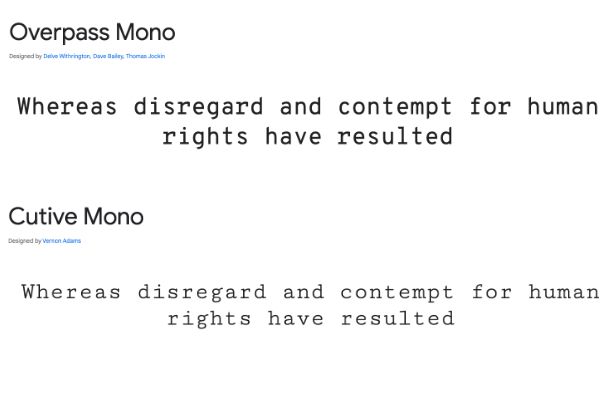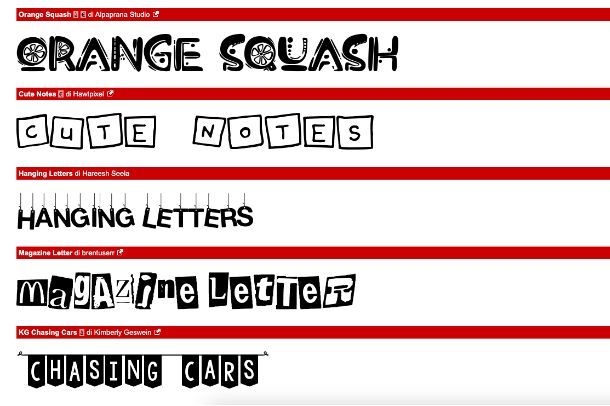
Migliori font per siti Web
Stai realizzando un piccolo sito Web per promuovere la tua attività o come tuo semplice portfolio personale, e grazie ai consigli presenti nel mio tutorial sei riuscito a realizzare il tutto senza particolari problemi.
Adesso, dunque, stai finalizzando il tutto, andando ad apportare le ultime modifiche grafiche. Infatti, nonostante le immagine e i colori utilizzati ti soddisfino pienamente, non puoi dire la stessa cosa del font utilizzato, per cui hai deciso di cambiarlo. Dato che non avevi idea su quale font utilizzare, hai deciso di metterti sul Web alla ricerca dei migliori font per siti Web e ti sei imbattuto in questo mio tutorial sull'argomento.
Posso dirti che sei capitato nel posto giusto. Nel corso di questa guida ti parlerò dei migliori font da utilizzare sui siti Web e ti mostrerò anche dove poterli scaricare gratuitamente. Tutto quello che devi fare è metterti comodo, prenderti cinque minuti di tempo libero e proseguire con la lettura dei prossimi paragrafi. Non mi resta che augurarti una buona lettura!
Font per siti Web gratis
Non vedi l'ora di scoprire quelli che sono i migliori font per siti Web gratis? Allora non devi far altro che dare un'occhiata ai prossimi paragrafi, dove ti parlerò di quelli più utilizzati e in voga per realizzare un sito Web dalla grafica accattivante.
Font Sans Serif
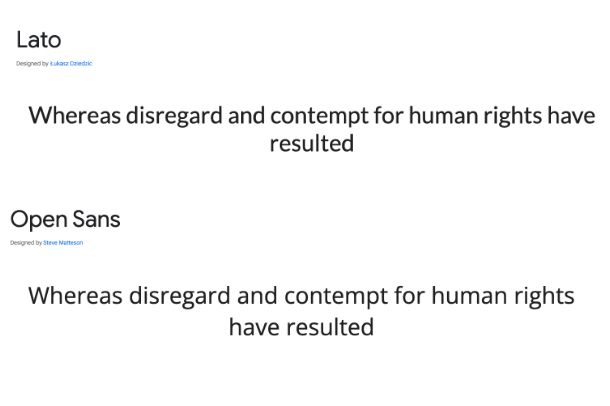
I font Sans Serif rappresentano una famiglia di caratteri dall'aspetto moderno, ma la tempo stesso sono semplici e lineari. Per questo motivo, sono perfetti per realizzare un sito Web tramite il quale si vuole trasmettere professionalità, come ad esempio quello di un'azienda. Inoltre, hanno un alto livello di leggibilità e rendono il tuo sito Web al passo con i tempi.
- Lato – uno dei font più utilizzati nel Web grazie alla sua alta leggibilità che lo rende perfetto per l'utilizzo su tutti i tipi di dispositivi.
- Open Sans – font commissionato da Google ottimizzato per la leggibilità su siti Web e dispositivi mobili, infatti viene utilizzato di default su Mozilla Firefox e nell'app Telegram Desktop.
- Helvetica – font molto classico ed elegante, che ha avuto grande successo negli ani settanta. Tantissime aziende utilizzano questo carattere nel proprio logo, tra cui Microsoft e Motorola.
- Montserrat – font che combina eleganza a elementi di rotondità, che prende ispirazione da vecchi manifesti e insegne del quartiere Montserrat di Buenos Aires.
- Arial – font molto famoso, utilizzato principalmente su PC, infatti è utilizzato all'interno di Microsoft Windows e macOS.
- Noto Sans — font classico utilizzato per qualsiasi tipologia di sito Web, dotato di più stili corsivi, spessori e larghezze.
- Oxygen – font che trasmette innovazione e professionalità, creato come parte del progetto KDE su Linux.
- Roboto – carattere sviluppato da Google, una scelta sicura per qualsiasi Web designer. Utilizza delle forme in gran parte geometriche, ma con alcune curvature che rendono la lettura più piacevole.
- Josefin Sans – font che si ispira ai disegni geometrici degli anni '20, che combina geometrie ed eleganza, con un tocco vintage, consigliato per l'uso in formati più grandi.
- Futura – font molto antico, infatti il suo sviluppo risale addirittura al 1927. Avendo un'altezza piuttosto bassa, è sicuramente più adatto per l'utilizzo all'interno del corpo del testo, piuttosto che sui titoli.
- Questrial – font moderno che rende altamente leggibile il testo, per cui è molto adatto per quei siti Web dotati di pagine con tanto testo e per i titoli.
- Archivo – font progettato per far risaltare le parole chiave e i titoli e che supporta oltre 200 lingue.
- Century Gothic – font in stile geometrico basato sul cerchio e sul quadrato, destinato a usi a caratteri grandi come intestazioni.
- Exo – font dall'aspetto futuristico, ma con un design elegante. Si tratta di un carattere molto versatile, infatti ha 9 pesi, ognuno con una vera versione in corsivo. Funziona bene per testi di piccole e medie dimensioni.
Font Serif
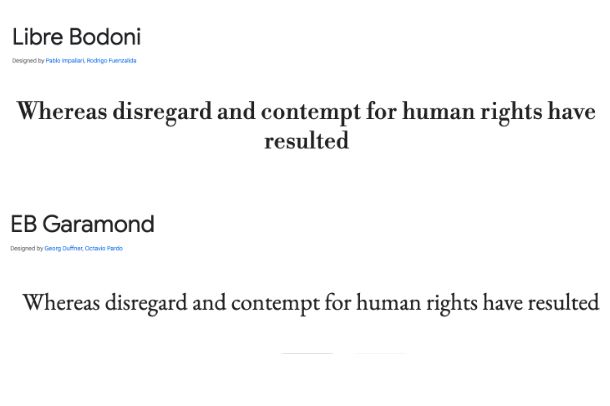
I font Serif, invece, rappresentano una famiglia di caratteri abbastanza decorati. Per tale motivo, sono più adatti per utilizzarli su titoli e intestazioni dio un sito Web, ma ti consiglio di evitarne l'utilizzo per testi molto lunghi.
- Times New Roman – uno dei font più diffusi ed eleganti presenti sul Web, grazie soprattutto al suo alto livello di leggibilità, ma sicuramente non uno dei più moderni in circolazione. Viene spesso utilizzato su Microsoft Word e Google Documenti.
- Libre Bodoni – tipo di carattere disegnato dall'italiano Bodoni nel 1798, contraddistinto dal contrasto tra linee spesse e sottili. Tuttavia, questa alternanza tra linee spesse e sottili, può creare problemi di leggibilità.
- Palatino – uno dei caratteri più usati e copiati, considerato uno dei più facili da leggere. Viene utilizzato principalmente nei testi.
- Abril Fatface – font che si ispira ai caratteri di titolazione pesanti utilizzati nei manifesti pubblicitari in Gran Bretagna e Francia del XIX secolo. Si tratta di un carattere particolare e moderno, perfetto per siti Web che vogliono attirare l'attenzione.